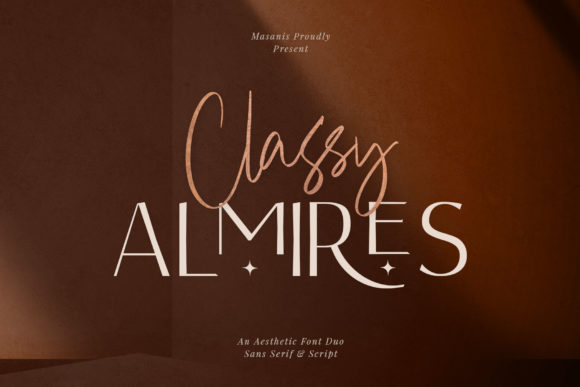
Classy Almires
Wenn Sie nach hochwertigen Assets wie Classy Almires suchen, ist dieses Premium-Paket eine fantastische Wahl für Ihre kreativen Projekte.
Egal, ob Sie POD-Produkte (Print on Demand), Hochzeitseinladungen oder Social-Media-Grafiken erstellen, Classy Almires ist die ideale Wahl.